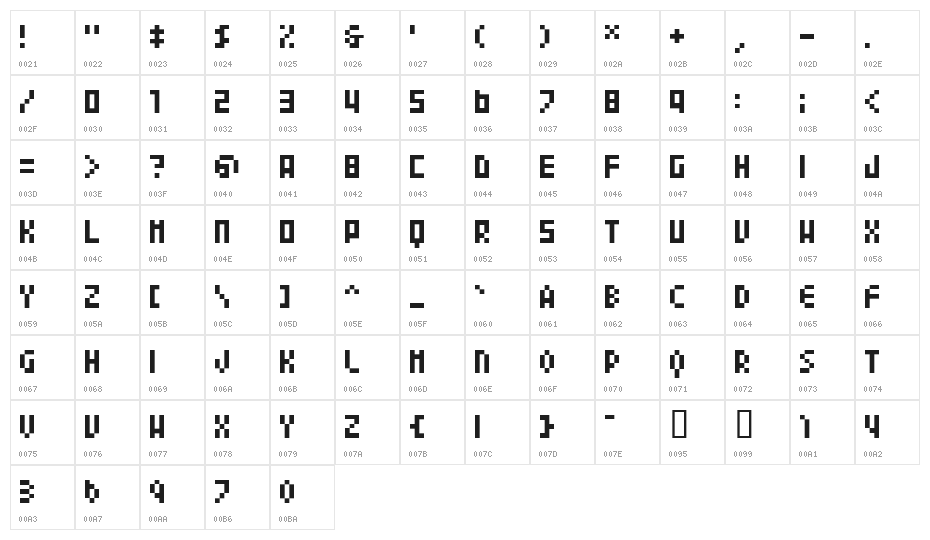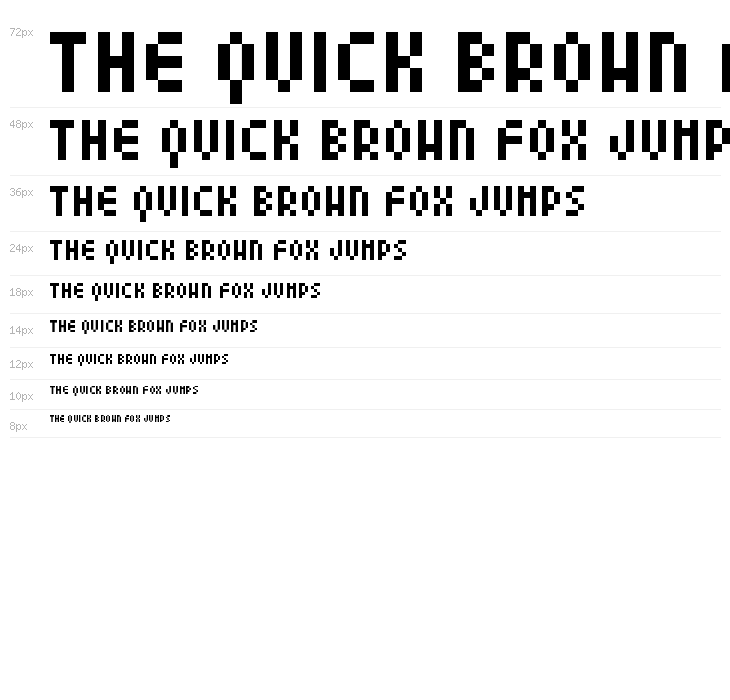
04b24 Font
| Stile generale | Retro, Digital |
| Caso d'uso | Headlines, Logos, Digital Art |
| Progetti proposti | Ideal for retro video game designs, tech-themed posters, digital art projects, and any creative work that seeks to evoke a sense of nostalgia for early computing. |